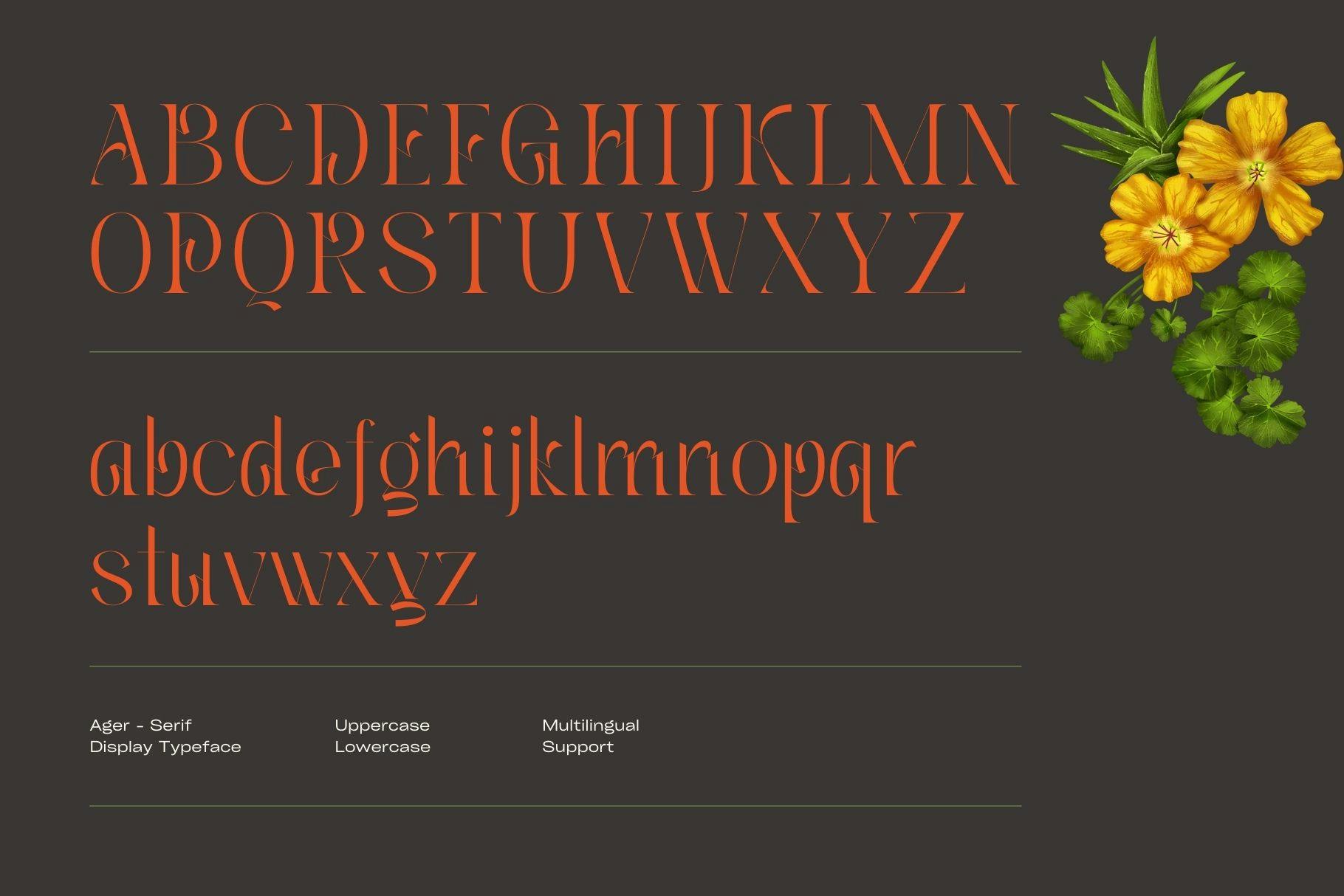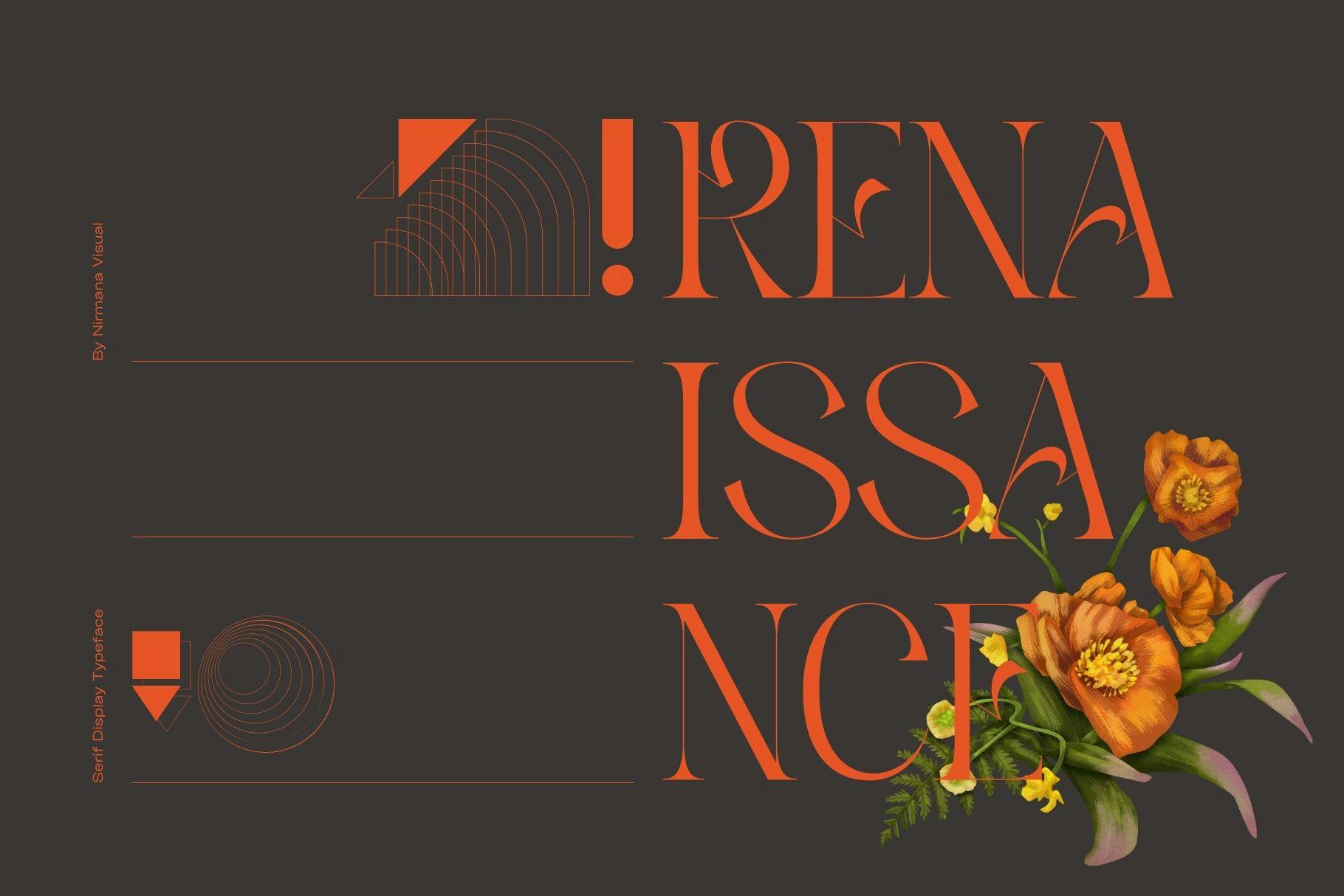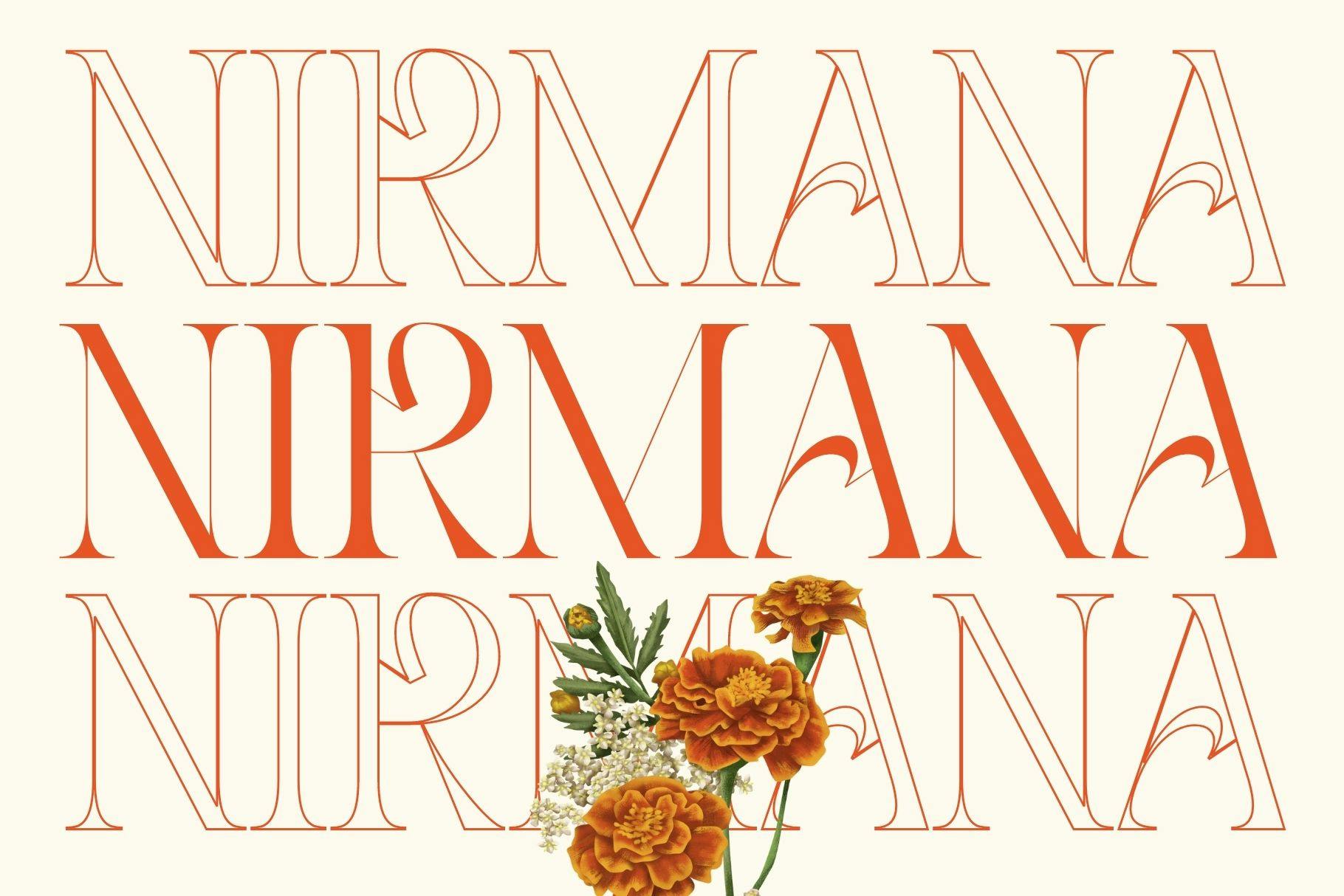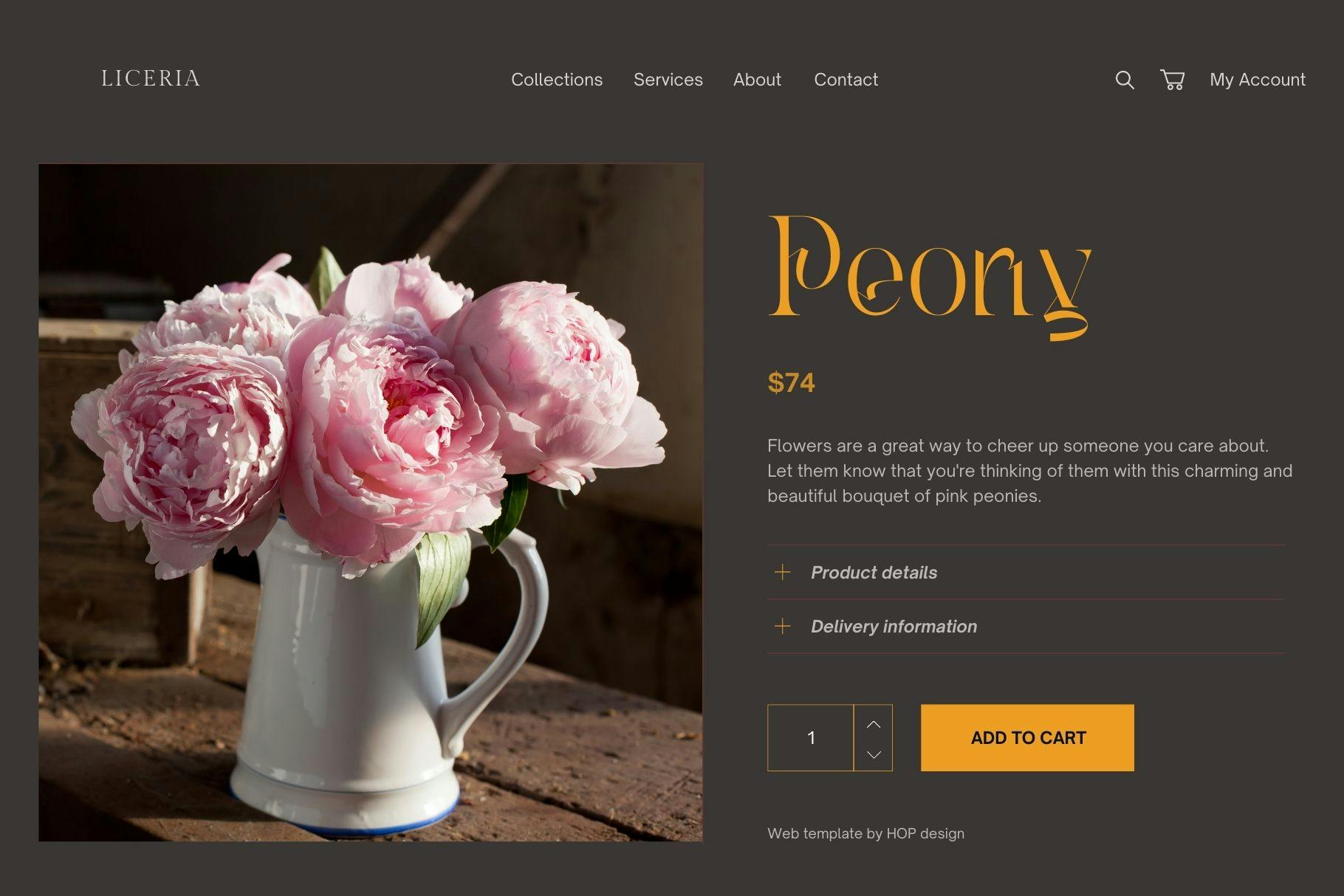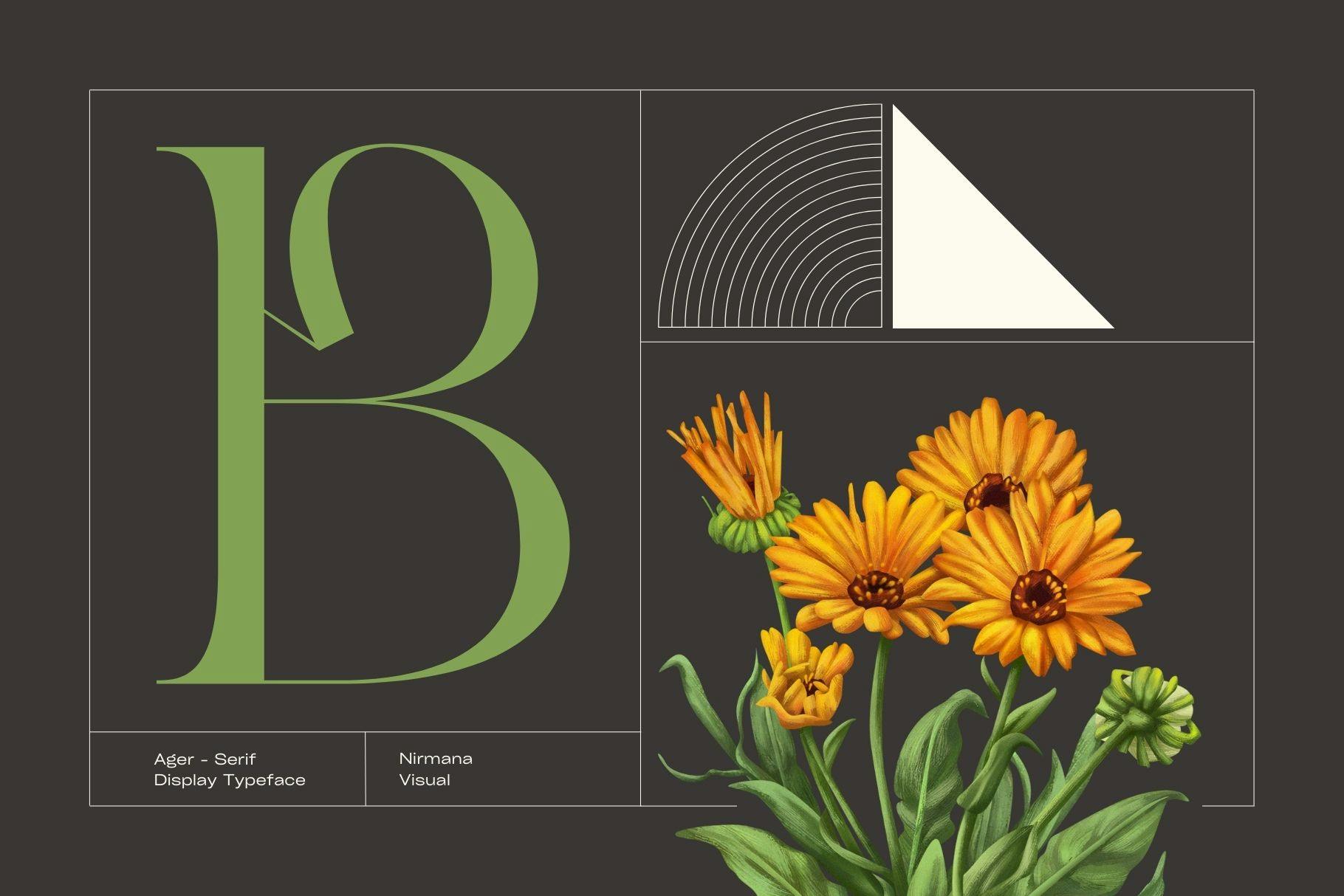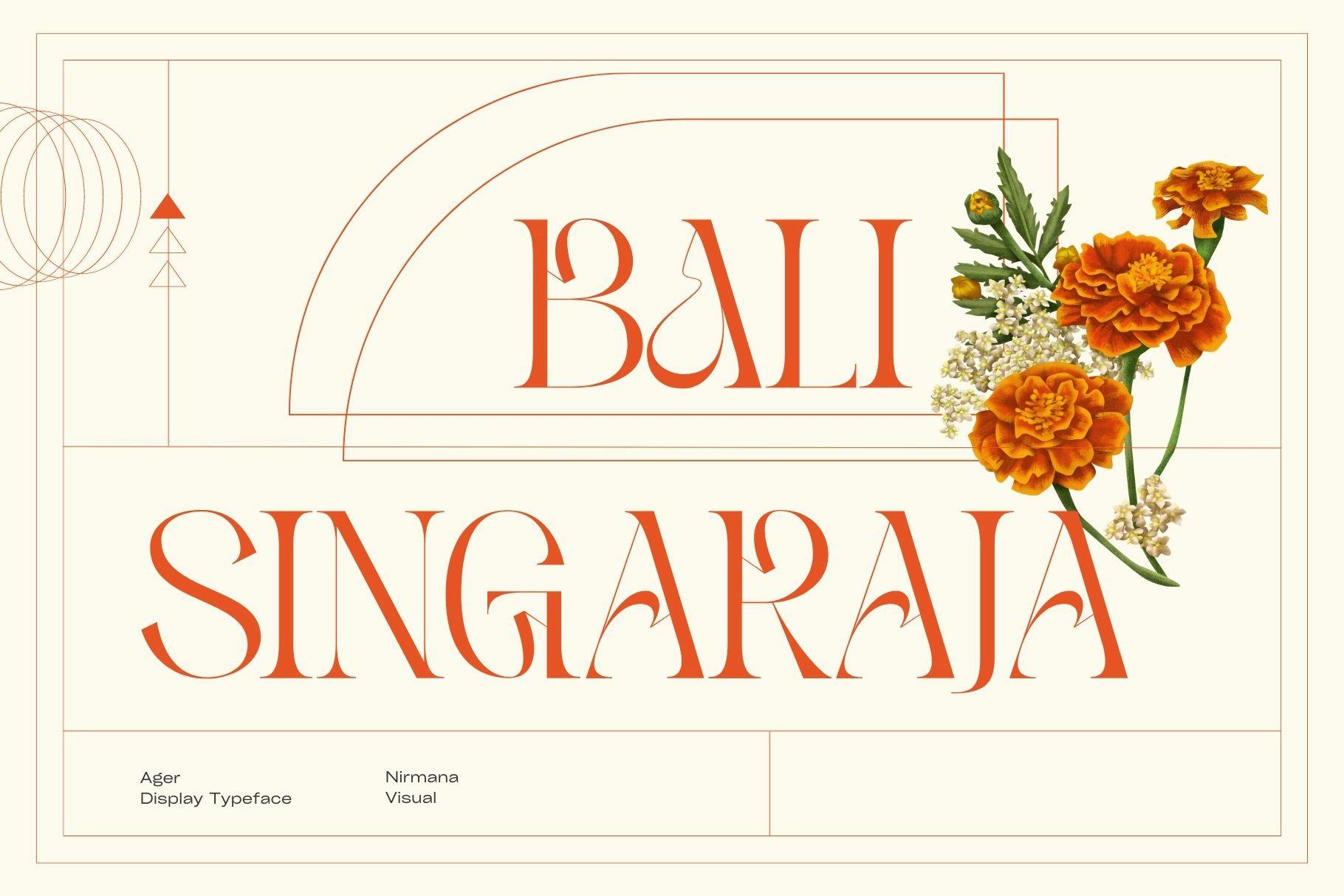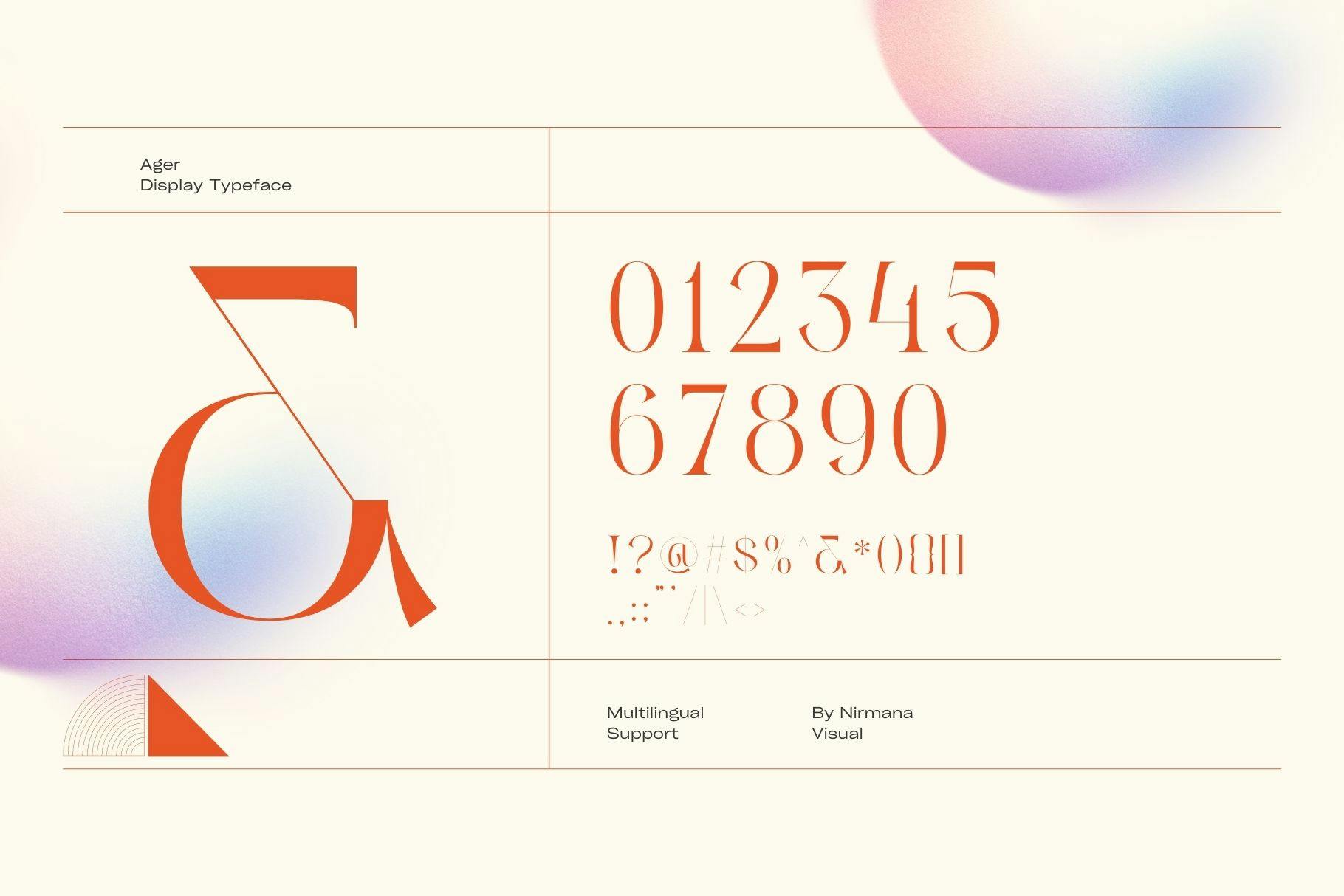
Ager با الهام از دوران طراحی آرت نوو ایجاد شده است. این فونت زیبای تایپوگرافی، هماهنگی فوقالعادهای را برای تنوع پروژههای طراحی از جمله لوگو و برندینگ، پستهای شبکههای اجتماعی، تبلیغات و طراحی محصولات ارائه میدهد.